Laura Meseguer comparte su mirada sobre la tipografía en el festival literario Gutun Zuria
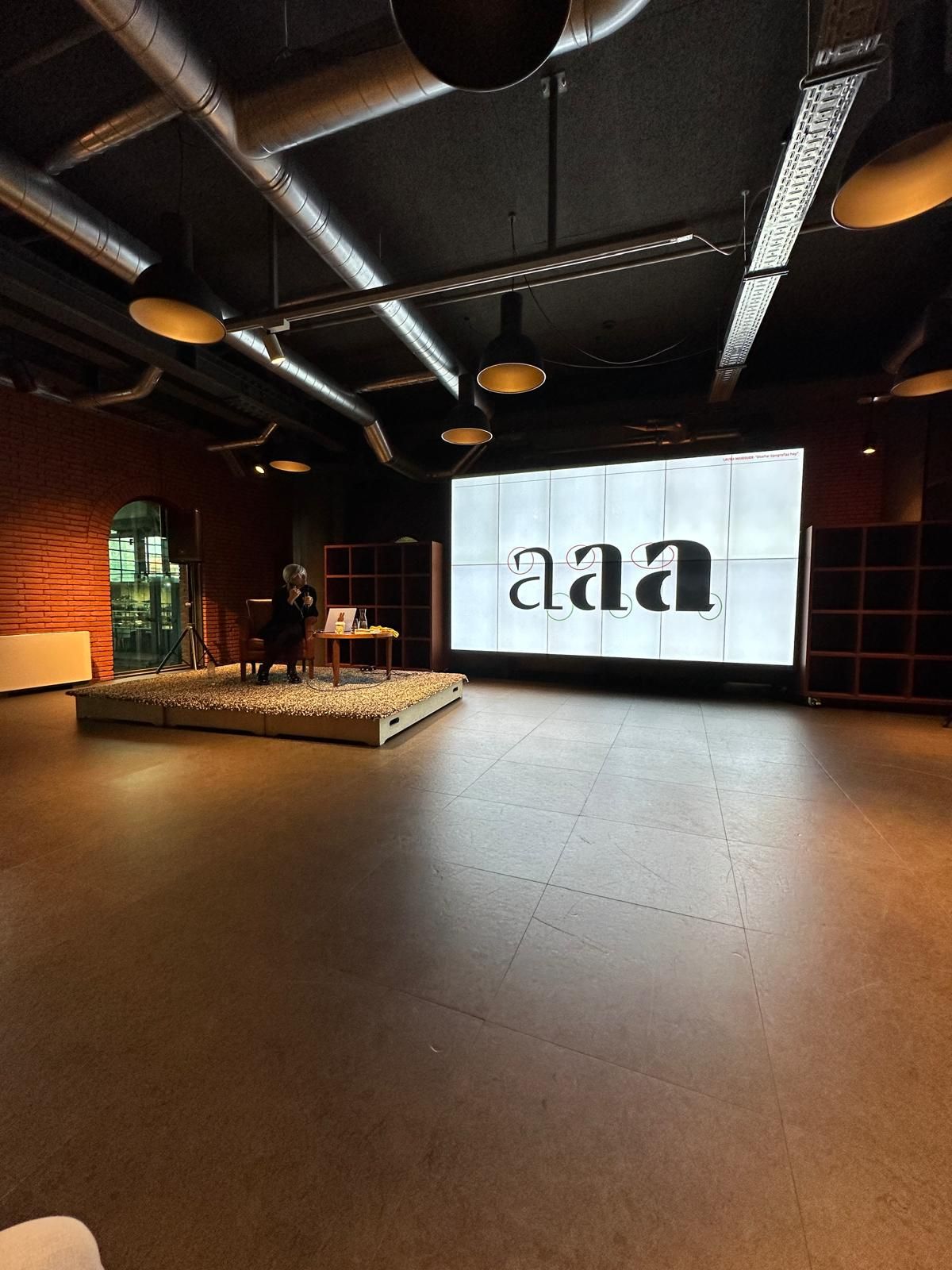
Laura Meseguer, docente del Máster en Diseño Editorial y Publicaciones Digitales de ESDESIGN, Escuela Superior de Diseño de Barcelona, perteneciente a Planeta Formación y Universidades, participó en la última edición de Gutun Zuria, el Festival Internacional de las Letras organizado por Azkuna Zentroa en Bilbao.
En el marco del programa del festival, Meseguer impartió una masterclass y una charla centradas en la tipografía, en las que abordó el papel de las letras como elemento esencial en la construcción del discurso visual y editorial. A través de ejemplos y reflexiones sobre el diseño tipográfico, invitó a los asistentes a observar las letras desde una nueva perspectiva, entendiendo su capacidad para transmitir significado, ritmo y personalidad en los proyectos gráficos.
El encuentro reunió a una audiencia formada por amantes de la literatura, el diseño y la cultura visual, generando un espacio de intercambio entre profesionales de distintos ámbitos creativos. Durante el festival, Meseguer también pudo coincidir con autoras, comisarias y consultoras vinculadas al mundo editorial, en un entorno que favorece el diálogo entre disciplinas.
La participación de Laura Meseguer en Gutun Zuria refuerza el vínculo entre diseño y literatura, destacando el papel de la tipografía como una herramienta clave para interpretar y comunicar el lenguaje escrito. Desde ESDESIGN celebramos su presencia en un evento que promueve la reflexión cultural y el intercambio de ideas en torno al mundo de las letras y el diseño.